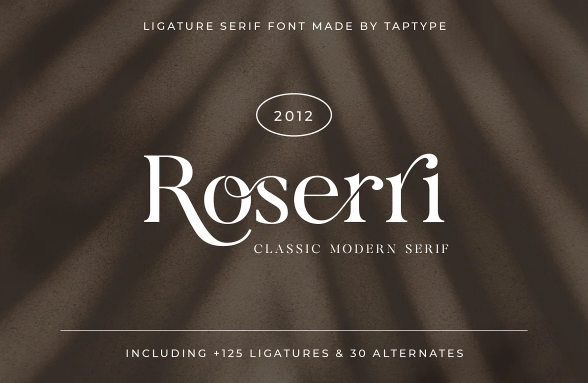
[Creativemarket] Roserri Font (2021)
Roserri - стильный современный шрифт с богатой вязью Serif. Минималистский характер, позволяющий легко редактировать дизайн. Он идеально подходит для брендинга, свадебных приглашений и открыток, а также, возможно, для какого-то проекта.
125 специальных лигатур